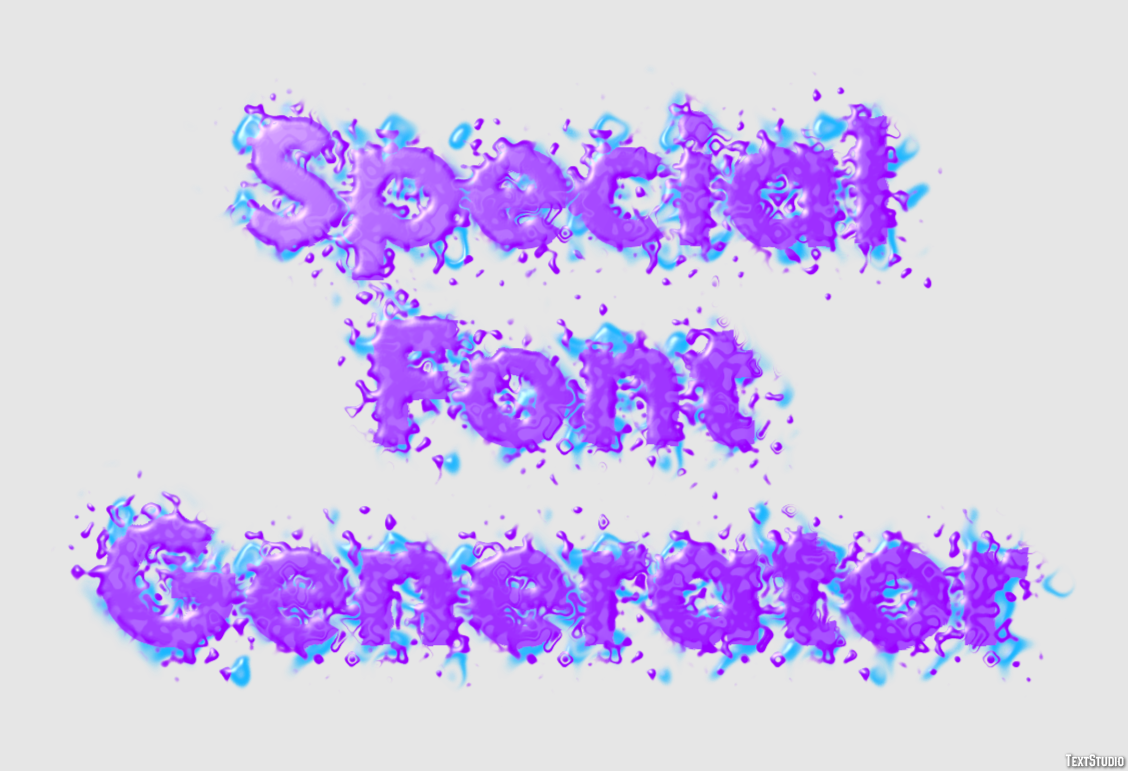
Spectaculair Splash teksteffect
Special Font Generator Tekst Effect
Special Font Generator Tekst EffectSpectaculair Splash Teksteffect
Lettertype effect ontwerpen Special Font Generator.